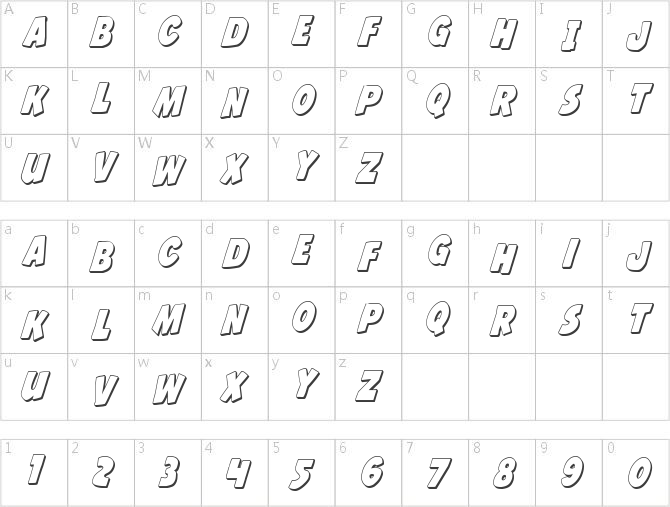
Jack's Candlestick 3D Condensed
Jack's Candlestick 3D Condensed介绍
Jack's Candlestick 3D Condensed字体字库是一款让人赏心悦目、百看不厌的英文字体,适合各类广告和产品包装设计应用,字体大小0.13MB,格式为ttf字体,上传用户是顺新广告?,作者/版权方为未知
Jack's Candlestick 3D Condensed效果图